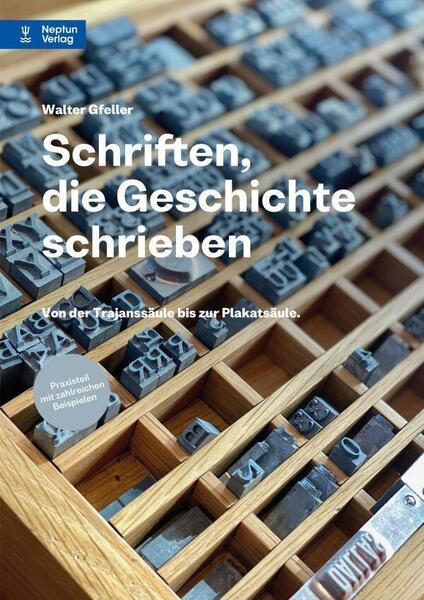
Schriften, die Geschichte schrieben
Mit ein paar Federstrichen die Welt erreichen: Eine Geschichte europäischer Schriften
Die Macht der Schrift: Im Bruchteil einer Sekunde kann uns ein Schriftbild in eine bestimmte Zeit oder kulturelle Sphäre katapultieren und damit eine Botschaft nicht nur unterstreichen, sondern geradezu vorwegnehmen. Schrift ist jedoch nicht nur Transportmittel – sie zu kreieren, schneiden, digitalisieren und im richtigen Werk gezeichnet oder gedruckt einzusetzen ist selbst eine Kunst.
Von der Entwicklung dieser Kunst berichtet Walter Gfeller in seinem kürzlich erschienenen Band „Schriften, die Geschichte schrieben“. Er beginnt dabei in der Antike, springt aber recht schnell zu Gutenberg und konzentriert sich dann auf die im west- und südeuropäischen sowie deutschsprachigen Raum entwickelten und genutzten Schriften.
Der Sprung von handgeschriebenen Hieroglyphen, Skripten und Vervielfältigungen zur Erfindung des Buchdrucks war immens. Doch er setzte weiterhin ein künstlerisches Auge und handwerkliches Geschick voraus. Worin dies besteht, was die Eleganz, Schwungkraft, die Text-Lesbarkeit oder Eignung als Auszeichnungsschrift verschiedenster Schriften ausmacht, beschreibt Gfeller ausführlich anhand Hunderter Beispiele in einem Anhang, der zusammen mit einer kommentierten Bibliographie fast 600 der insgesamt 750 Buchseiten umfasst. Zugleich wartet er mit einer Menge an Informationen und Geschichte(n) über die Künstler, Schriftschneider, Setzer und Drucker auf, die zur Vielfalt der heute verfügbaren Schriften und Fonts beigetragen haben. Denn Kunst findet sich nun ebenfalls im digitalen Raum, auch in der gekonnten Digitalisierung vorhandener Schriften und Schöpfung modernisierter Formen. Gfeller gelingt mit seiner Sammlung ein Überblick, der sowohl breit als auch tief zu schürfen sucht und Lust darauf macht, weiter zu schauen.
Doch mit der Fülle nutzbarer Designs wiegt umso schwerer die Frage nach dem Content. Denn was Gfeller aus Johan Huizingas Buch „Erasmus“ über den Wechsel zum Buchdruck zitiert, ist im Zeitalter von Social Media höchst aktuell: „Das Bewusstsein, man könne mit seinem Wort sofort die ganze Welt erreichen, ist ein Reiz, der unbewusst die Art der Äußerung beeinflusst […]“. Egal, in welchen Lettern oder Fonts sie erscheint.
Inmitten der Menge an Gestaltungsmerkmalen, Zeichnungen und Lebensläufen scheint dieser große Zusammenhang von Inhalt, Rahmen und Schriftgestalt etwas aus dem Blick zu geraten. An seinen Schriftmustern legt Gfeller ihn zwar mit Blick auf konkrete Verwendungen immer wieder detailreich dar. Doch was haben einzelne Schriften geschichtlich bewirkt, wie wurden sie wahrgenommen, verwendet, (miss-)verstanden und eingeordnet? Diese Fragen, evoziert durch den Titel, bleiben unbeantwortet, und jenseits weniger Anekdoten wird der Bogen von der Schrift zur Geschichte kaum geschlagen. Dabei ist das Geschehen um den „Antiqua-Pionier“ Augereau überaus interessant, der mit 200 Druckern, Verlegern und Buchhändlern 1534 wegen einer Plakataktion (mit der er nichts zu tun hatte) verhaftet wurde und dann einem Justizmord zum Opfer fiel. Von der Macht der reinen Verbreitung des Wortes und der Furcht davor ließe sich in einer Geschichte der Schriftentwicklung sicher mehr erzählen.
Und auch davon, warum die Fraktur, für die offenbar das Herz des Verfassers schlägt, so ambivalente Gefühle auslöst und seit dem 2. Weltkrieg nur noch wenig gefragt ist. Zu wenig praktikabel? Schwer lesbar? Oder geschichtlich verbrannt? Man hat den Eindruck, dass der Autor seine persönliche Sicht und speziell sein Bedauern über das Verschwinden der gebrochenen Schriften vor allem durch die Schriftmuster-, d.h. die Textauswahl im Anhang wiedergibt und so Dritte für sich sprechen lässt. Leider fehlt es dabei an der Einordnung; nur sehr punktuell finden sich Hinweise auf das Verwerfen und dann wieder den expliziten Gebrauch von Fraktur und Schwabacher durch den NS. Gerade letzteres aber bestimmt die heutige Wahrnehmung qua Assoziation und ist womöglich relevanter für Nutzungsentscheidungen als die im Anhang abgebildeten (und im Text nur typographisch kommentierten) Argumente der besseren europäischen Geläufigkeit der Antiqua. (Die etliche Beispiele französischer u.a. Texte in gebrochenen Schriften auch etwas entkräften.) Hier wäre eine historische Einordnung jenseits der rein gestalterischen Aspekte nützlich gewesen. Zumal sich auch Zitate von Rudolf Koch unter den Beispielen finden, die in puncto deutsch-nationalistischer Selbstüberhöhung recht deutlich sind. Aus der Schweizer Sicht des Autors mag das weniger gewichtig und die Abwendung von den gebrochenen Schriften eher technisch motiviert erscheinen. Für ein v.a. auch in Deutschland vertriebenes Buch, das immerhin sich deutscher statt Schweizer Rechtschreibung (Nutzung von ß) bedient, das zumal darauf rekurriert, wie „Schriften […] Geschichte schrieben“, wäre ein genauerer Blick auf diesen zentralen Aspekt wünschenswert gewesen. So ist es doch eher eine „Geschichte der Schriften“.
Um die Menge des Materials auch gestalterisch zu bändigen, hat sich Gfeller eigene typographische Entscheidungen getroffen. Die sorgfältige Verwendung inhaltlich korrespondierender Schrifttypen für bestimme Absätze und das Einfügen hervorgehobener Lettern im Text verdient große Bewunderung. Gerade in einem Band über Schriftgestaltung wünschte man sich jedoch Konsistenz auch optisch im Satzbild, den Überschriftenkategorien und der Gesamtgestaltung – kurz: entsprechende Unterstützung durch den Verlag.
Trotz dieser offenen Wünsche ist das Buch eine anspruchsvolle Lektüre – oder genauer ein Werk zum Nachschlagen, vielleicht sogar Nachzeichnen – für Fachleute und all diejenigen, die Freude an der Vielfalt von Schriften und ihrer Gestaltung haben.
Untertitel: Von der Trajanssäule bis zur Plakatsäule
Autor(en): Walter Gfeller